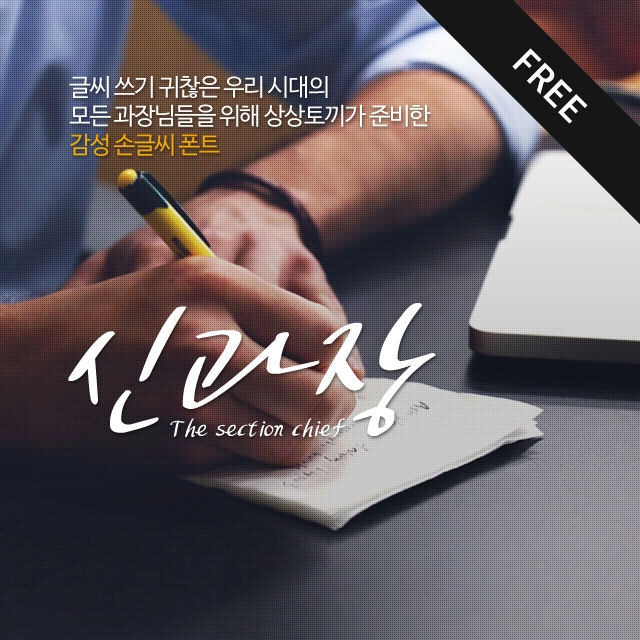
신과장
컴퓨터 자판 두드리는 것도 귀찮고, 손글씨 쓰기는 더 귀찮은 우리 과장님들을 위해, 신과장
컴퓨터 자판 두드리는 것도 귀찮고, 손글씨 쓰기는 더 귀찮은 우리 과장님들을 위해 만들어진 감성 폰트 <신과장>은 폰트를 만드는 캘리그래퍼로 불리는 상상토끼 용이 작가의 디지털 캘리그라피 펜글씨를 기초로 해서 만들어진 폰트입니다. 소중한 글씨로 멋진 폰트를 만들어준 상상토끼 용이 작가에게 또 한번 감사의 마음을 전합니다. |